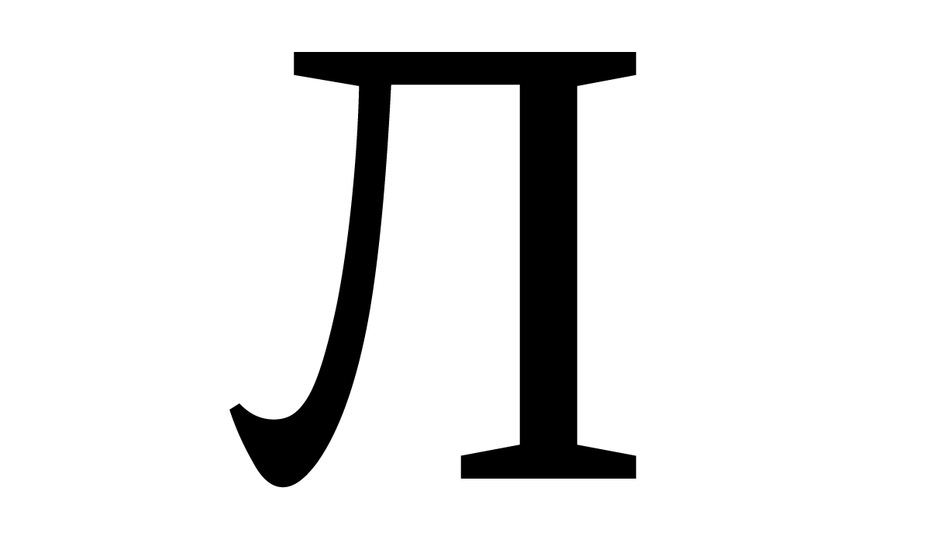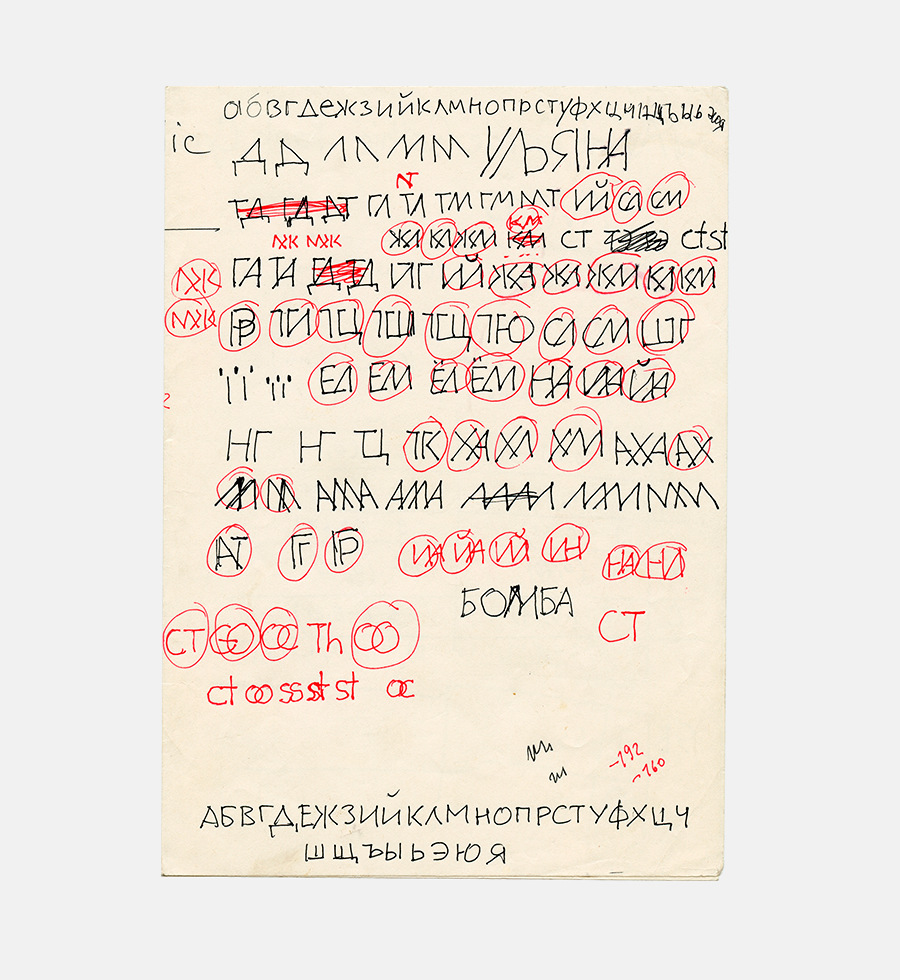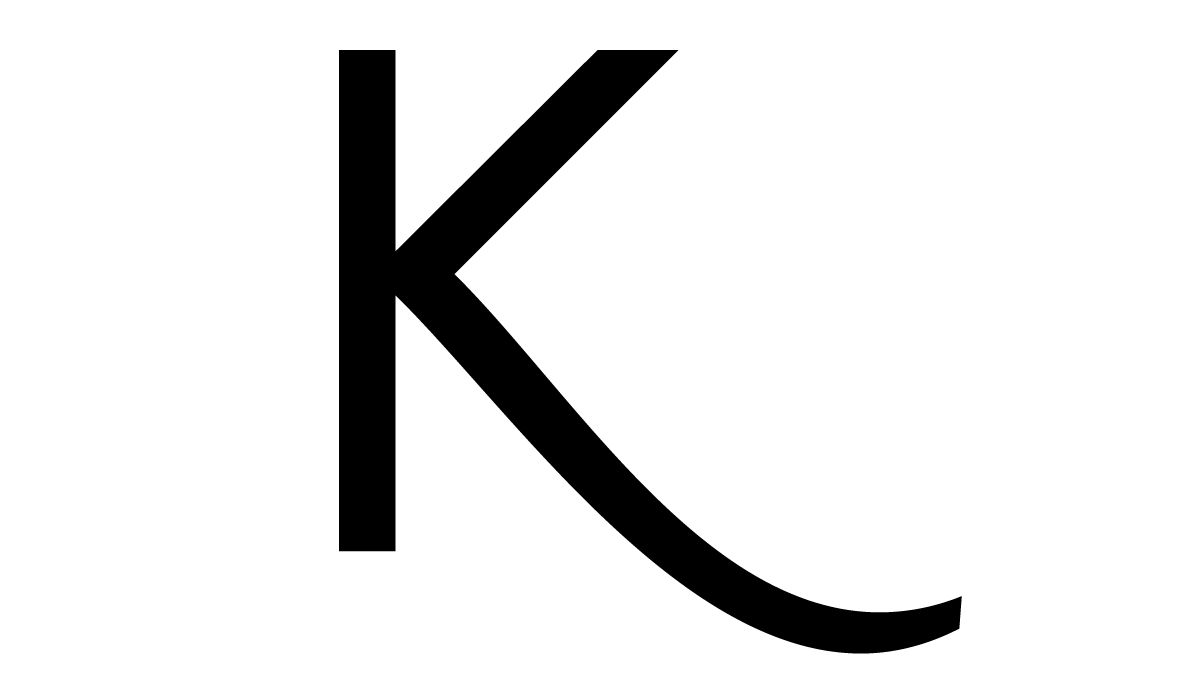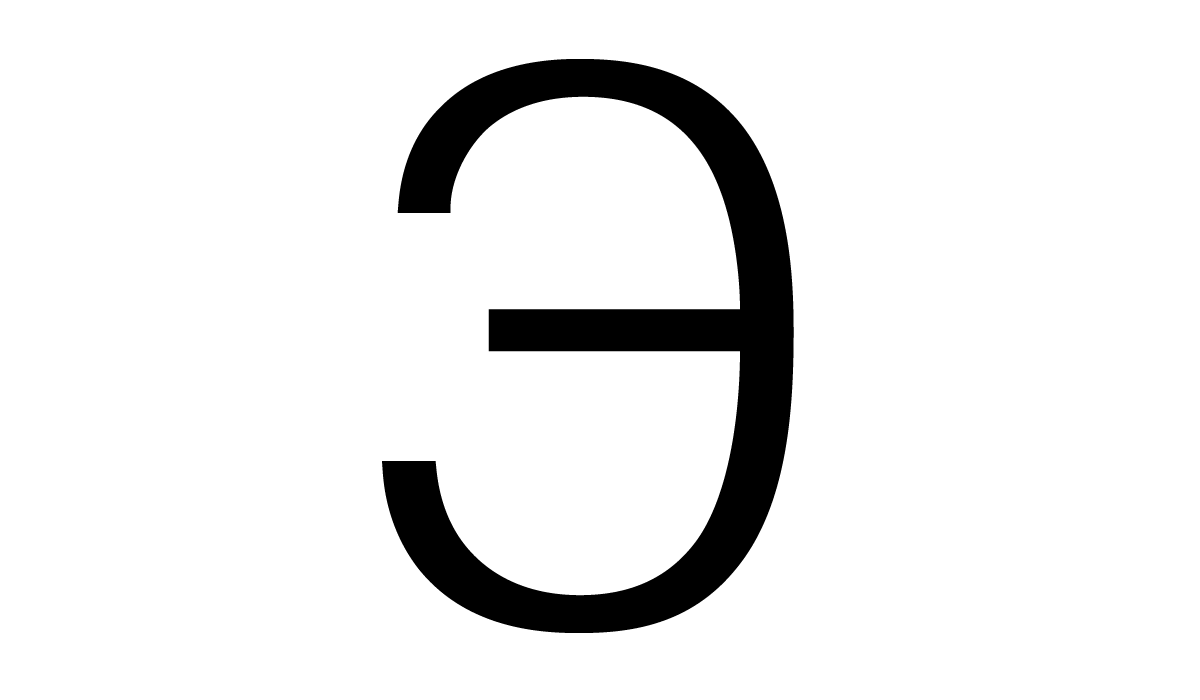
10 шрифтов Владимира Ефимова
6 мая ис­пол­ни­лось 70 лет со дня ро­жде­ния шриф­то­во­го ди­зай­не­ра Вла­ди­ми­ра Ефи­мо­ва (*6 мая 1949 †23 фе­вра­ля 2012). Мы вы­бра­ли 10 шриф­тов Вла­ди­ми­ра Ве­не­дик­то­ви­ча и со­про­во­ди­ли их ком­мен­та­ри­я­ми, ко­то­рые он за­пи­сал в 2010 го­ду для вы­став­ки «Шриф­то­вых дел ма­стер» в Му­зее ар­хи­тек­ту­ры. Поз­же они бы­ли по­ме­ще­ны в не­боль­шом ка­та­ло­ге, вы­пу­щен­ном ком­па­ни­ей ParaType. Мы пуб­ли­ку­ем ком­мен­та­рии с не­боль­ши­ми со­кра­ще­ни­я­ми. Спи­сок на­чи­на­ет­ся со шриф­тов, ко­то­рые не все­гда свя­зы­ва­лись в со­зна­нии чи­та­те­лей с «ака­де­ми­че­ским» сти­лем Вла­ди­ми­ра Ефи­мо­ва. Меж­ду тем его ки­рил­ли­за­ции шриф­тов Джо­на­та­на Бар­н­бру­ка, сту­дии «Эми­гре» и дру­гих про­грес­сив­ных в 90-е го­ды сло­во­ли­тен и се­го­дня оста­ют­ся ма­стер­ски­ми и сме­лы­ми про­ек­та­ми, о ко­то­рых мы счи­та­ем нуж­ным на­по­мнить.
☛ ITC Avant Garde Gothic
Вла­ди­мир Ефи­мов: «Ава­нгард Го­тик — глав­ный шрифт ITC, ко­то­рым они без­ум­но гор­ди­лись. До то­го, как мы на­ча­ли офи­ци­аль­ную ра­бо­ту над этим шриф­том, Мак­сим Жу­ков уже за­став­лял ме­ня ри­со­вать eгo ва­ри­ан­ты для раз­ных язы­ков. Из­да­тель­ство „Мир“ вы­пус­ка­ло ли­те­ра­ту­ру на рус­ском и ино­стран­ных язы­ках. Часть этих язы­ков бы­ла вос­точ­ная. Бы­ли из­да­ния для Ин­дии, Аф­га­ни­ста­на и дру­гих стран. А по­сколь­ку я ра­бо­тал в ла­бо­ра­то­рии шриф­тов осо­бых гра­фи­че­ских форм, я был свя­зан с вос­точ­ны­ми шриф­та­ми. И Мак­сим мне за­ка­зы­вал над­пи­си в сти­ле Аван­гар­да для ин­дий­ской пись­мен­но­сти де­ва­на­га­ри, гре­че­ские, араб­ские.
У ме­ня с этим Аван­гар­дом бы­ли уже ка­кие-то лич­ные от­но­ше­ния — он мне снил­ся но­ча­ми. Я на­чал ду­мать, как мне от не­го из­ба­вить­ся. Но тут от­крыл­ся „Па­ра­граф“, и я ту­да пе­решёл, так как в от­де­ле на­бор­ных шриф­тов всё за­кон­чи­лось и за­кры­лось. А в 1990 го­ду Мак­сим ска­зал: „Да­вай ри­суй ки­рил­ли­че­скую вер­сию Аван­гар­да, так как ру­ко­вод­ство IТС ре­ши­ло не рис­ко­вать и не де­лать гре­че­ский, араб­ский, ин­дий­ский и иврит­ский Аван­гард, а про ки­рил­ли­че­ский, вздох­нув­ши, ска­за­ло: пусть бу­дет“.
У Лю­ба­ли­на бы­ло в Аван­гар­де на­ри­со­ва­но мно­го ли­га­тур, он хо­тел на но­вом уров­не по­вто­рить то, что ко­гда-то сде­лал Гу­тен­берг. И мы ре­ши­ли, что раз уж вы­пус­ка­ем ком­плект на­чер­та­ний в фор­ма­те OpenТу­ре, то на­до вос­поль­зо­вать­ся его пре­иму­ще­ством и до­ба­вить ту­да мно­го-мно­го ли­га­тур. Мы сде­ла­ли все ли­га­ту­ры, ко­то­рые на­ри­со­вал Лю­ба­лин, а по­том бы­ли сде­ла­ны ки­рил­ли­че­ские ана­ло­ги, и по­лу­чи­лось их очень мно­го! Прав­да, я не знаю, за­чем это нуж­но, но ма­ло ли, вдруг ко­му-ни­будь по­на­до­бит­ся».
☛ Mason Sans
Вла­ди­мир Ефи­мов: «Это был за­каз из­вест­ной пив­ной ком­па­нии „Стел­ла Ар­туа“. У них был раз­ра­бо­тан фир­мен­ный стиль на осно­ве Ма­со­на, и ко­гда они от­кры­ва­ли свое про­из­вод­ство и пред­ста­ви­тель­ство в Рос­сии, им по­на­до­бил­ся ки­рил­ли­че­ский Ма­сон. Они за­ка­за­ли се­те­во­му агент­ству раз­ра­бот­ку фир­мен­но­го сти­ля, а те са­ми не ста­ли де­лать ки­рил­ли­че­скую вер­сию шриф­та, а обра­ти­лись к нам. Мне при­шлось не­ко­то­рое вре­мя этим за­ни­мать­ся. Этот шрифт поз­во­ля­ет про­де­лы­вать с ним вся­кие мо­ди­фи­ка­ции. Мне бы­ло до­воль­но ин­те­рес­но с ним во­зить­ся: он на­столь­ко дик по сво­е­му основ­но­му ре­ше­нию в ла­ти­ни­це, что мне нуж­но бы­ло най­ти ту же сте­пень ди­ко­сти в ки­рил­ли­це. У бук­вы А, на­при­мер, бы­ло два ва­ри­ан­та: од­на — нор­маль­ная, тре­уголь­ная (не очень нор­маль­ная, но по­чти), а у дру­гой круг­лые бо­ка и острая вер­ши­на, по­лу­ча­ет­ся как буд­то бо­е­го­лов­ка или сна­ряд. Это на­зы­ва­ет­ся „ожи­валь­ная фор­ма“. Я сде­лал та­кие ва­ри­ан­ты ещё для Л и Д…
Ко­гда я при­нёс уже до­воль­но про­дви­ну­тую на­ри­со­ван­ную вер­сию Ма­со­на на­ше­му за­каз­чи­ку для ут­вер­жде­ния, он, че­ло­век до­воль­но мо­ло­дой и на вид ин­тел­ли­гент­ный, ска­зал: вот ка­кие шриф­ты бы­ли в ры­цар­ские вре­ме­на. Тут я пе­ре­пу­гал­ся и ска­зал, что в ры­цар­ские вре­ме­на во­об­ще-то го­ти­ка бы­ла, а эта эк­лек­ти­ка к ры­цар­ским вре­ме­нам ни­ка­ко­го от­но­ше­ния не име­ет. В об­щем, мы друг дру­га по­ня­ли».
☛ Raleigh
Вла­ди­мир Ефи­мов: «Был в Ан­глии, в эпо­ху ко­ро­ле­вы Ели­за­ве­ты, из­вест­ный че­ло­век — Уол­тер Рэлей (или Рей­ли). Фа­во­рит ко­ро­ле­вы, лич­ность за­ме­ча­тель­ная, как и мно­гие де­я­те­ли шекс­пи­ров­ских вре­мён. Он был по­эт и пи­рат, ор­га­ни­зо­вы­вал экс­пе­ди­ции в Аме­ри­ку, во­е­вал, пи­сал ис­то­рию Ри­ма, си­дя в тюрь­ме в Тау­э­ре. И, кста­ти, зна­ме­нит он на­столь­ко, что до сих пор в Тау­э­ре его ка­ме­ра со­хра­ня­ет­ся в ка­че­стве му­зея — ка­ме­ра из двух ком­нат с бал­ко­ном, там в об­щем-то не­пло­хо бы­ло жить… Он был од­ним из луч­ших пред­ста­ви­те­лей эпо­хи ко­ро­ле­вы Ели­за­ве­ты. Кон­чил он, прав­да, пло­хо — ему от­ру­би­ли го­ло­ву за го­су­дар­ствен­ную из­ме­ну, в ко­то­рой он был ни­как не по­ви­нен. И эту тра­ги­че­скую ис­то­рию я дол­жен за­кон­чить тем, что сам шрифт к Уол­те­ру Рей­ли ни­ка­ко­го от­но­ше­ния не име­ет.
Ис­то­рия это­го шриф­та до­ста­точ­но за­пу­тан­ная, и сна­ча­ла на­зы­вал­ся он со­вер­шен­но не так. Это был фир­мен­ный шрифт для Все­мир­ной вы­став­ки 1969 го­да в Монре­а­ле, в Ка­на­де, в од­ном на­чер­та­нии, и со­здал его ди­зай­нер Карп Дэйр. По­том на его осно­ве был сде­лан шрифт в двух на­чер­та­ни­ях (пря­мое и кур­сив), на­зван­ный Cartier. И опять же, я не уве­рен, что это бы­ло сде­ла­но по за­ка­зу этой са­мой зна­ме­ни­той юве­лир­ной фир­мы. Его кур­сив был со­здан на осно­ве ста­рых и очень ред­ких кал­ли­гра­фи­че­ских по­чер­ков, но в пер­во­на­чаль­ном шриф­те, ко­то­рый был сде­лан для Все­мир­ной вы­став­ки, кур­си­ва во­об­ще не бы­ло, он был до­ри­со­ван поз­же. Спу­стя ка­кое-то вре­мя, в 1977 го­ду, ан­глий­ский ди­зай­нер Ро­берт Нор­тон на осно­ве Cartier раз­ра­бо­тал этот са­мый шрифт в не­сколь­ких на­чер­та­ни­ях — от сверх­свет­ло­го до сверх­жир­но­го. Он-то и был на­зван Raleigh».
☛ English 157
Вла­ди­мир Ефи­мов: «Клас­си­че­ский ру­ко­пис­ный шрифт на­ча­ла XIX ве­ка, на­зы­ва­е­мый ан­глий­ским, или спен­се­ри­ан­ским. В пер­вом клас­се шко­лы пись­му по­хо­жим шриф­том ме­ня обу­ча­ли на уро­ках чи­сто­пи­са­ния. Мы пи­са­ли ме­тал­ли­че­ски­ми пе­рья­ми, ма­ка­ли их в чер­ниль­ни­цу, все хо­ди­ли в кляк­сах. Ме­ня так и не на­учи­ли тол­ком. Пи­шут­ся они остро­ко­неч­ным сталь­ным пе­ром, поз­во­ля­ю­щим уси­ли­вать на­жим, что де­ла­ет их кон­траст­ны­ми ру­ко­пис­ны­ми шриф­та­ми, ко­то­рые гар­мо­ни­ро­ва­ли с мод­ны­ми то­гда Ди­до и Бо­до­ни. Это ими­та­ция на­бор­ным спо­со­бом ру­ко­пис­ных шриф­тов. English 157 — шрифт по­лу­связ­ный: у не­го есть вы­хо­дя­щие кон­цы штри­хов, а вхо­дя­щих кон­цов нет. В осно­ве его ле­жит зна­ме­ни­тый кал­ли­гра­фи­че­ский шрифт не­мец­ко­го про­ис­хо­жде­ния под на­зва­ни­ем Englische Schreibschrift („Ан­глий­ский ру­ко­пис­ный шрифт“).
Я вы­брал eгo со­зна­тель­но, что­бы сде­лать ки­рил­ли­че­скую вер­сию: та­ко­го ти­па шриф­тов у нас не бы­ло, или бы­ли не очень ка­че­ствен­ные, с мо­ей точ­ки зре­ния. Я вос­поль­зо­вал­ся ста­ры­ми рус­ски­ми шриф­та­ми — до ре­во­лю­ции кал­ли­гра­фи­че­ские шриф­ты бы­ли очень по­пу­ляр­ны, и не­ко­то­рые из них бы­ли очень тон­ко и кра­си­во сде­ла­ны».